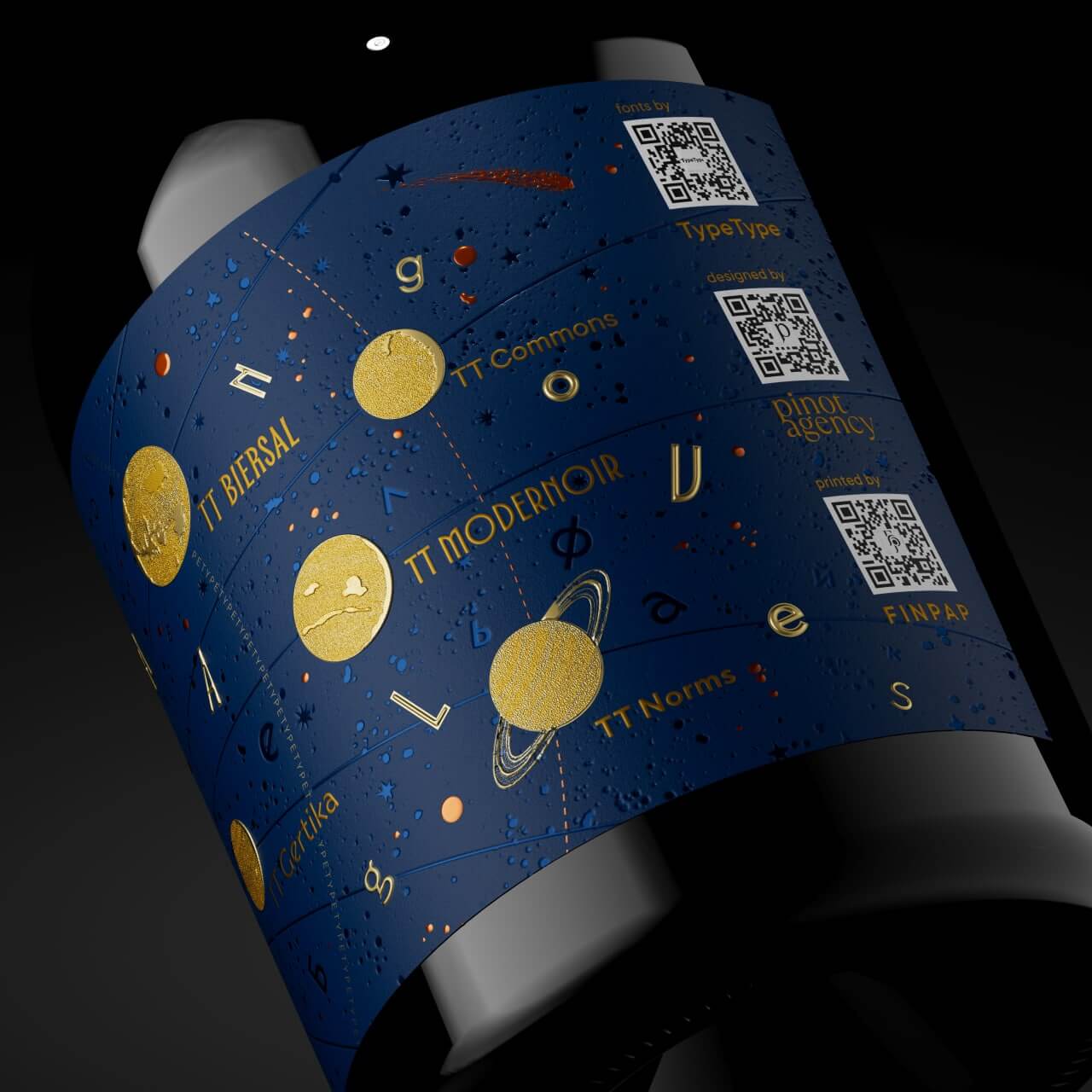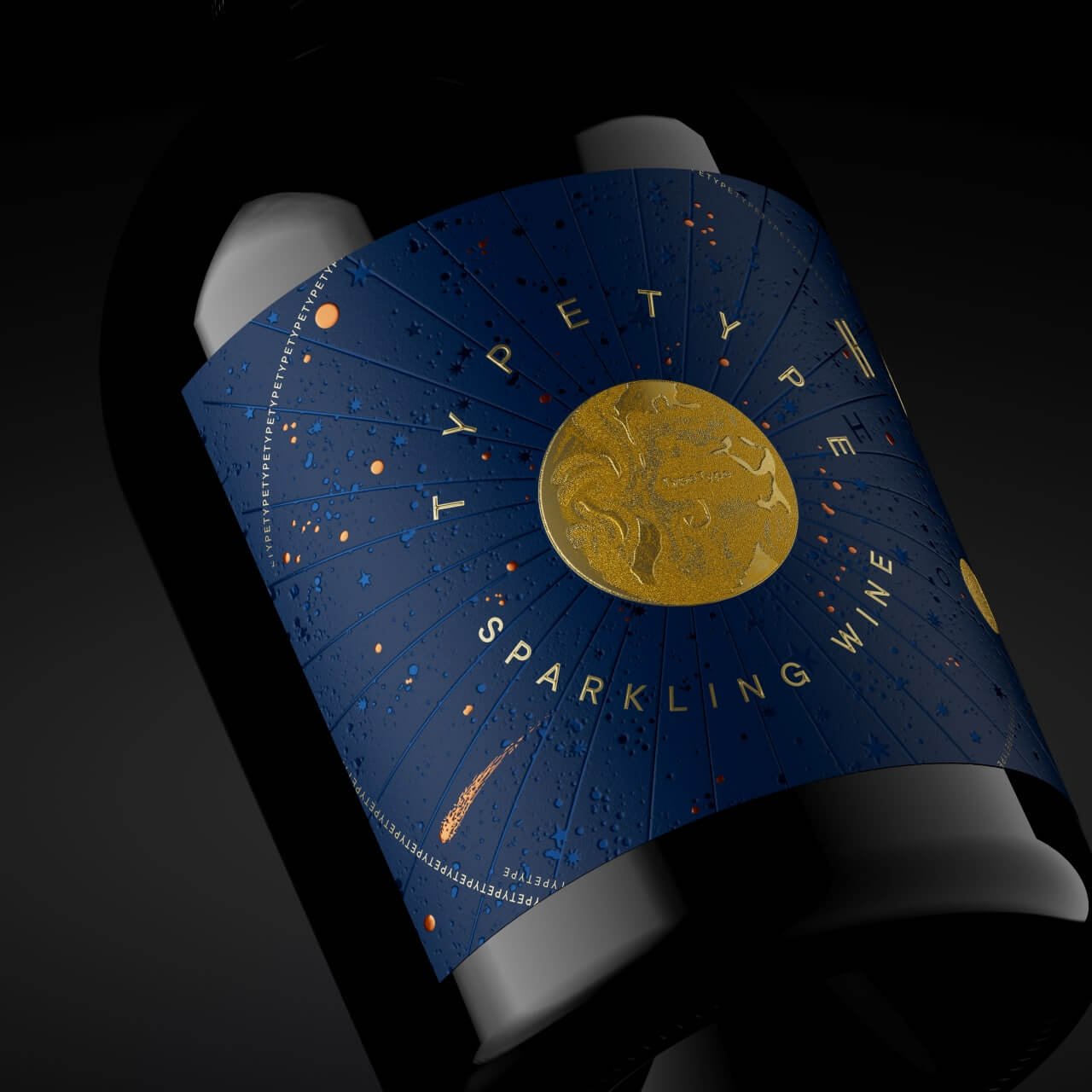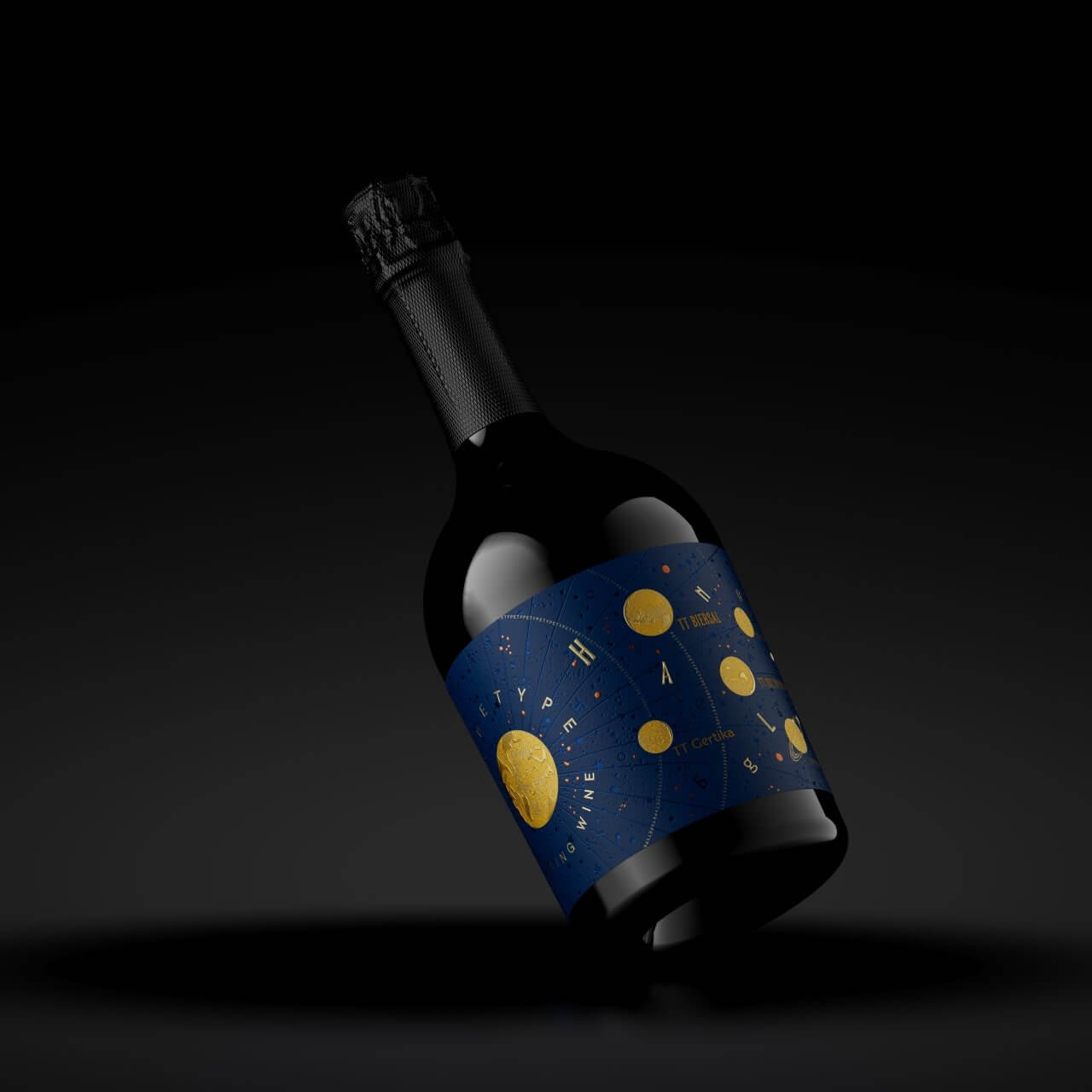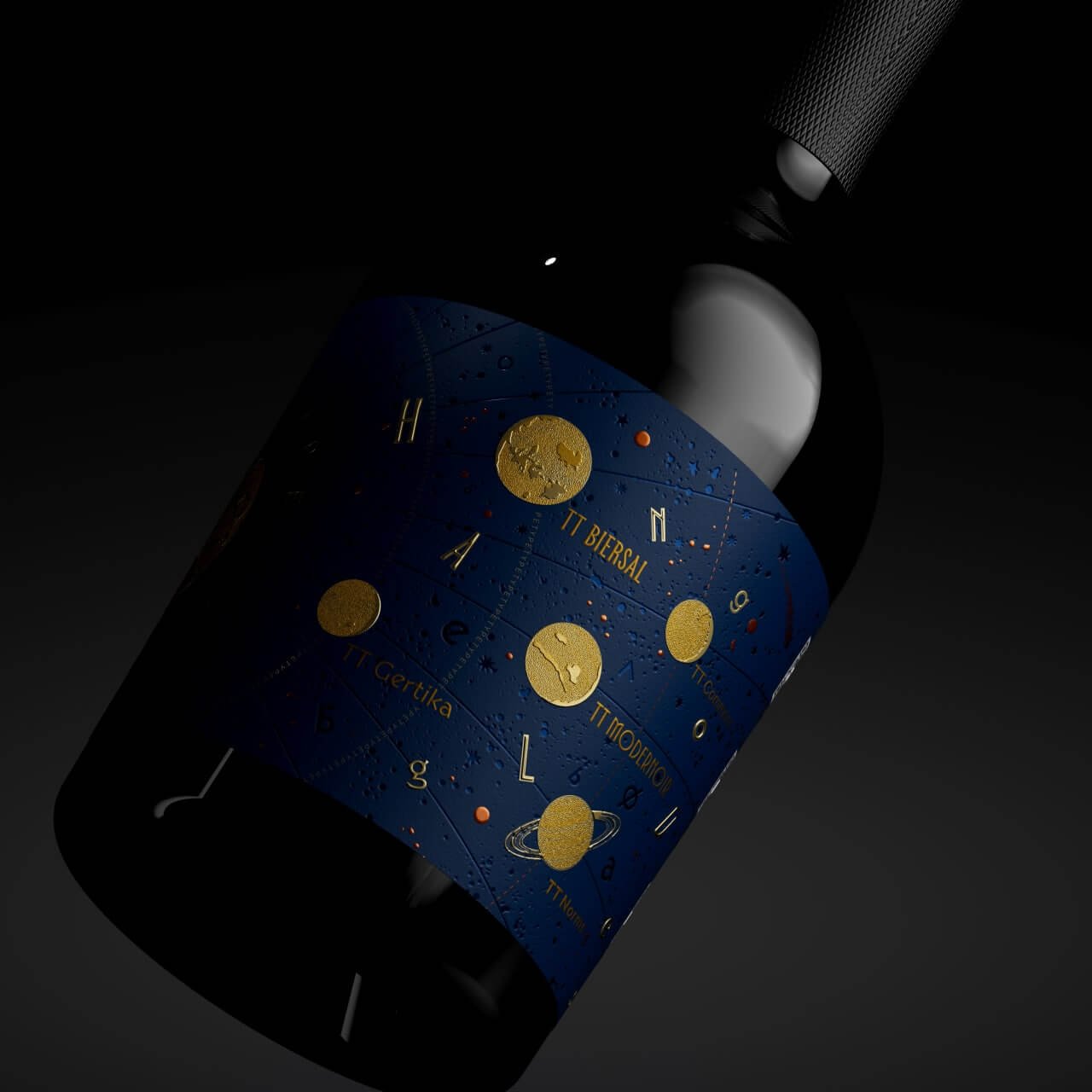
Font Universe - коллаборация с шрифтовой студией TypeType
Задача
Когда дело касается винного брендинга, всё начинается с этикетки. А где этикетка, там неизбежно шрифты — основа визуальной идентичности. Поэтому мы объединили силы с признанным
мастерами шрифтов, международной студией TypeType, чтобы создать нечто уникальное — вино планетарного масштаба, вдохновленное бесконечной вселенной шрифтов.
Решение
Шрифтовая студия TypeType — это те, кто создают шрифты, говорящие на языке идей, эмоций и культур. Их шрифты известны и любимы по всему миру, от монументальных и универсальных гигантов TT Norms и TT Commons, до сверхновых звезд TT Gertika и TT Modernoir. Каждый из них — как отдельная планета, живая и уникальная, а вместе они образуют целую шрифтовую вселенную. И наша этикетка стала звездной картой этой вселенной. Это карта, которая раскрывает шрифтовую галактику — и приглашает вас исследовать её, вращая бутылку в руках.
Но эта концепция не была бы полной без тактильного и визуального совершенства. Мы объединили усилия с Finpap, мастерами полиграфии, чтобы воплотить нашу идею в жизнь. Фактурная бумага Fasson Watermark стала основой, помогла создать глубину, тиснение с разными текстурами и многоуровневый конгрев придал этикетке тактильности, а медный гель добавил загадочного мерцания звезд во вселенной.
Результат
Шрифтовое вино — это не просто напиток, а арт-объект, который соединяет вкус и эстетику. Это коллаборация винного дизайна, типографики и полиграфии, создающая уникальный опыт.
Ощутите вино с новой стороны. Пусть дизайн расскажет вам свою историю, а вино станет её продолжением.